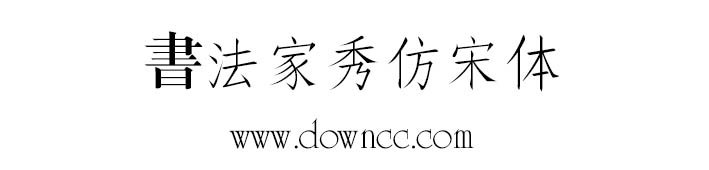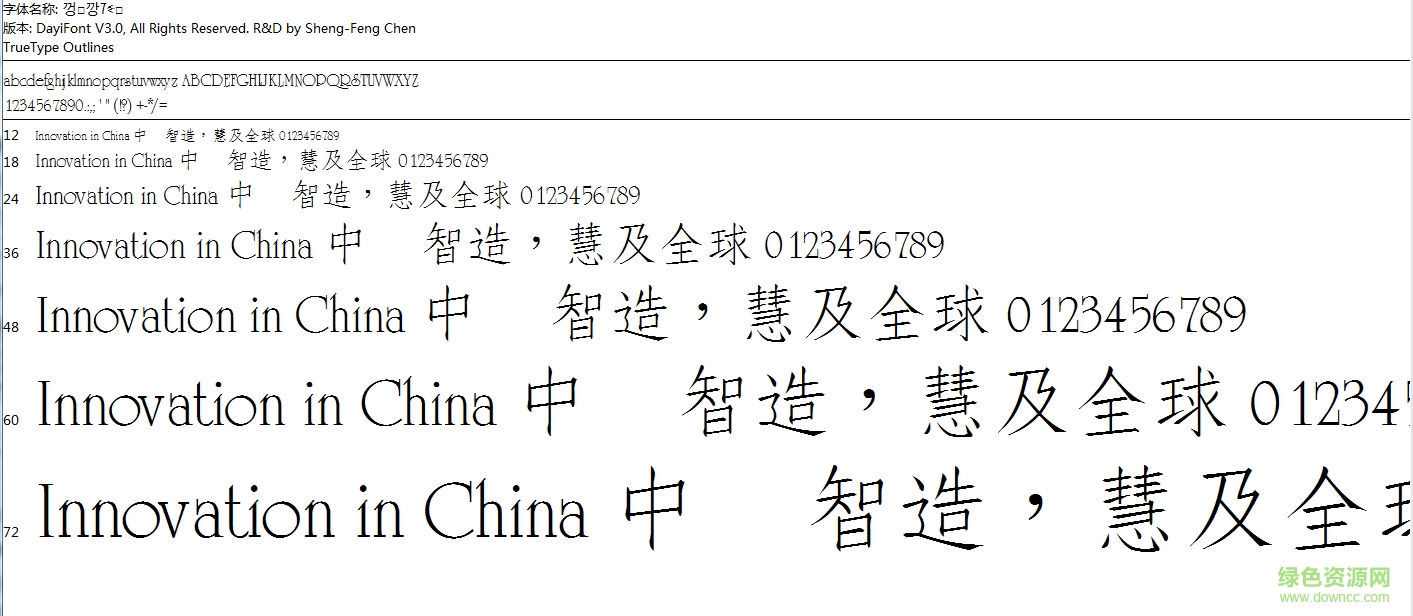
書法家秀仿宋是一款非常受書法愛(ài)好者喜歡的字體。該字體效果又如毛筆字,非常大氣,書寫時(shí)一氣呵成,相信你一定會(huì)喜歡這款字體的。那就快來(lái)綠色資源網(wǎng)下載吧!
書法家秀仿宋是印刷體的一種,因此書寫端正,清秀雅致,因?yàn)樽铋_(kāi)始是在木板上進(jìn)行雕刻,所有它的一筆一劃都非常的有力,是很多地方都在使用的字體。